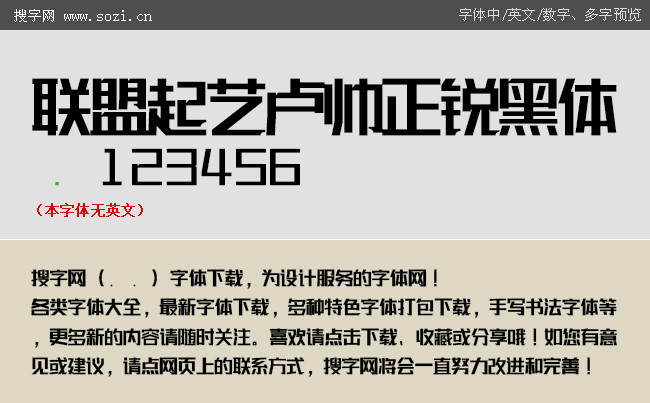
聯(lián)盟起藝盧帥正銳黑體
搜字網(wǎng)給大家提供一款聯(lián)盟起藝盧帥正銳黑體中文藝術(shù)字體下載,聯(lián)盟起藝盧帥正銳黑體是一款非常剛性的免費可商用標(biāo)題字體。這款字體筆觸粗實,字形厚重有力,但又不乏設(shè)計感,整體感覺非常不錯。適用于大標(biāo)題、包裝設(shè)計、海報設(shè)計等應(yīng)用。